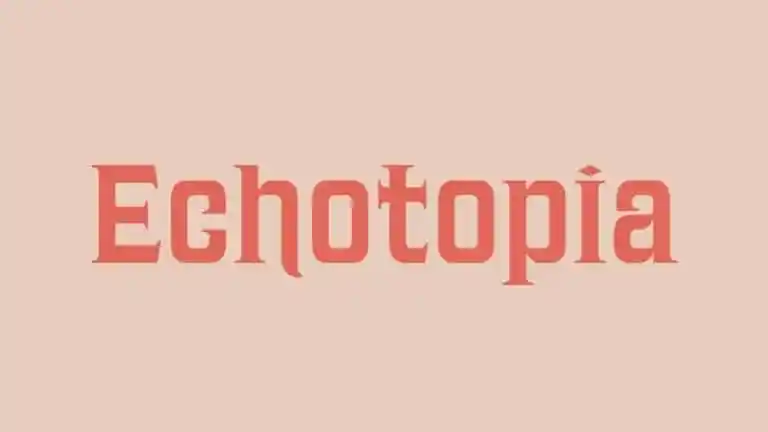
A fonte Echotopia Serif é uma tipografia serifizada vintage que surgiu do trabalho do designer erikkirtley. Inspirada no masthead de uma edição do The Echo publicado entre 1890 e 1900, conforme o Library of Congress, a Echotopia Serif captura o clima da arte typográfica dos anos 20, trazendo um toque nostálgico às páginas dos jornais passados. Com linhas sóbrias e texturas sutis, esta fonte serifizada remete ao design tipográfico das décadas de ouro do século XX. Ideal para revistas antológicas, sites históricos ou qualquer projeto que desejou manter um ar elegante e vintage, a Echotopia Serif é uma opção perfeita para quem busca adicionar um toque retrô à sua tipografia. Combinada com outras fontes serifadas do mesmo período, esta fonte permite criar layouts impecáveis que transmitem confiabilidade e estatura ao texto.